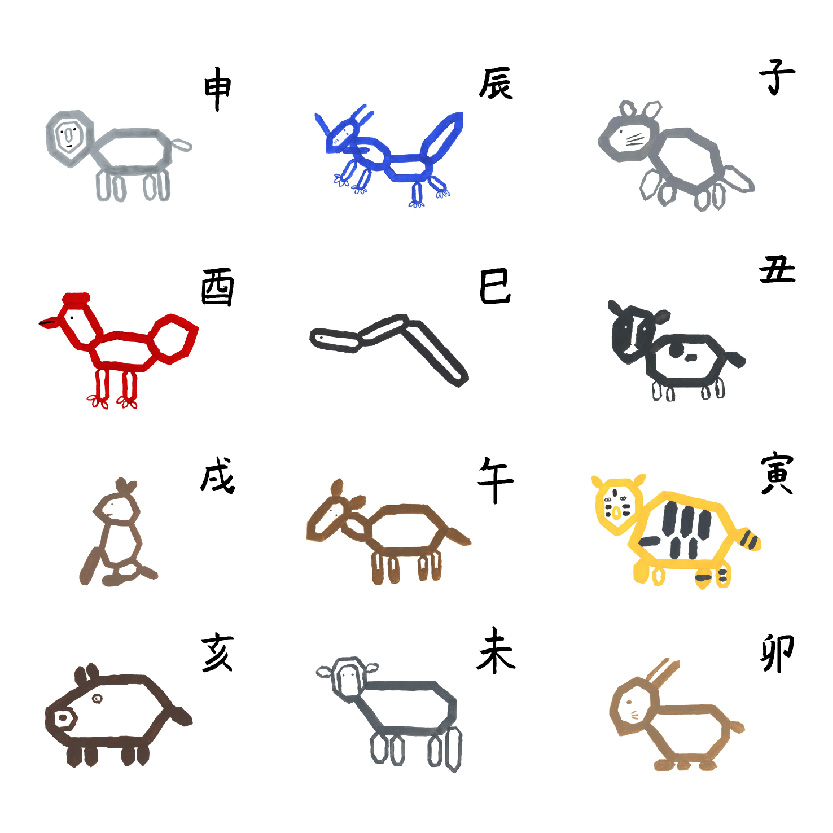
カクカクドウブツ
ツカイカタサマザマ、カクカクドウブツ
干支を七角形を使って描きました。文字は、墨と筆を使いました。絵の筆遣いが難しかったです。(澤田和弘)(澤田和弘)
私のお気に入りは、申です。お気に入りを見つけてみてください(いとうこゆき)(伊藤小雪)
昨年を踏まえ、年賀状に使えるデザインがあったらいいという話があったため描いていただきました。ただ動物を描くのではなく、カクカクにして一味加えました。澤田さんの几帳面さが出ている作品です。(ストライドクラブ)(ストライドクラブ)